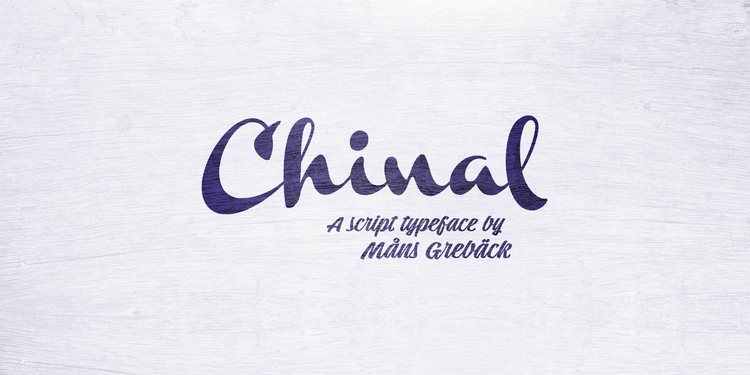
Introduzimos Chinal Font! Chinal é uma fonte tipográfica script que transmite harmonia. Desenvolvida pelo designer Måns Grebäck durante 2017, a famosa família de tipos contém quatro pesos complementares: Chinal Light, Chinal Medium, Chinal Bold e Chinal Black. Com sua vasta gama de caracteres de cerca de cem, Chinal suporta uma ampla variedade de idiomas. Além disso, o conjunto inclui múltiplas características do OpenType, como alternativas contextualizadas, um conjunto de caracteres alternativos estilizados, swashes, letras iniciais e finais, ornamentos e ligaturas. Este é mais que simplesmente uma fonte script; Chinal oferece flexibilidade para criar escrita de alta qualidade em qualquer projeto.